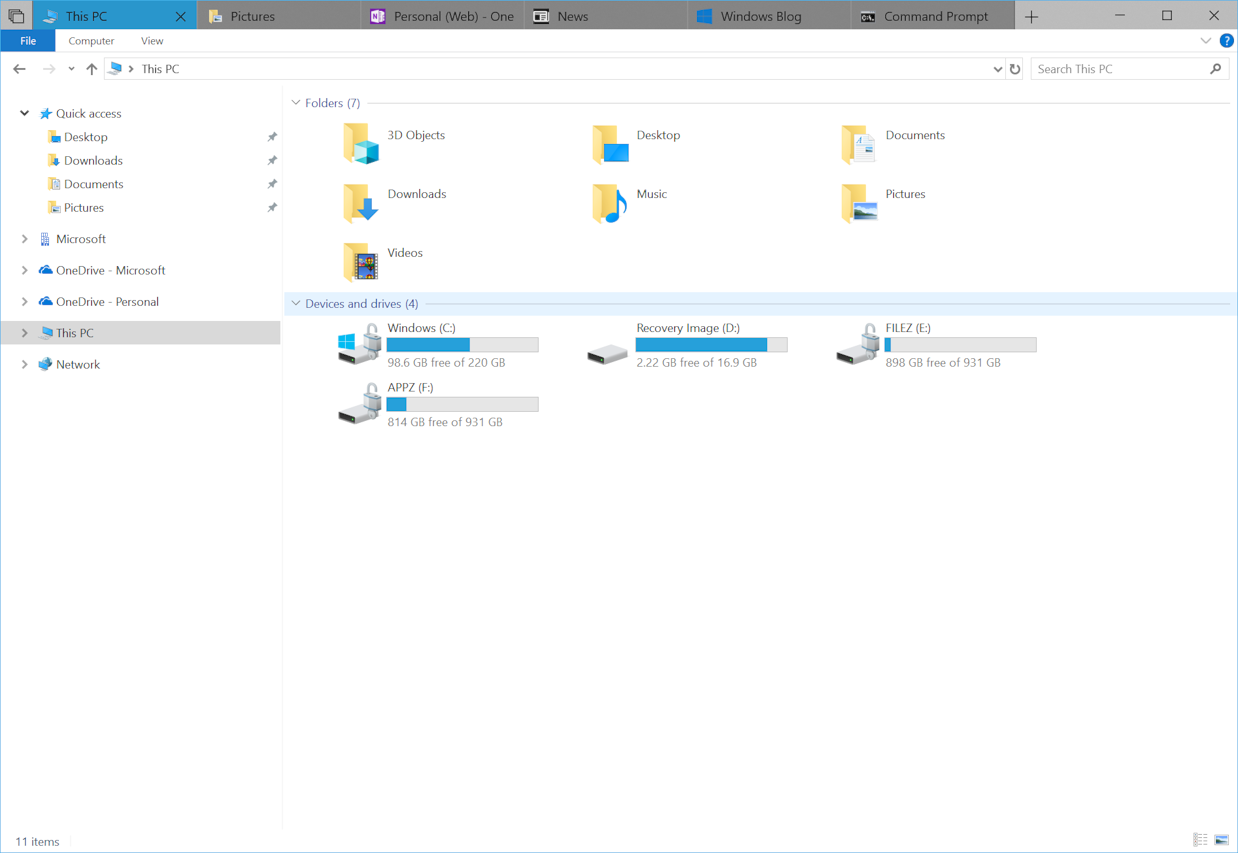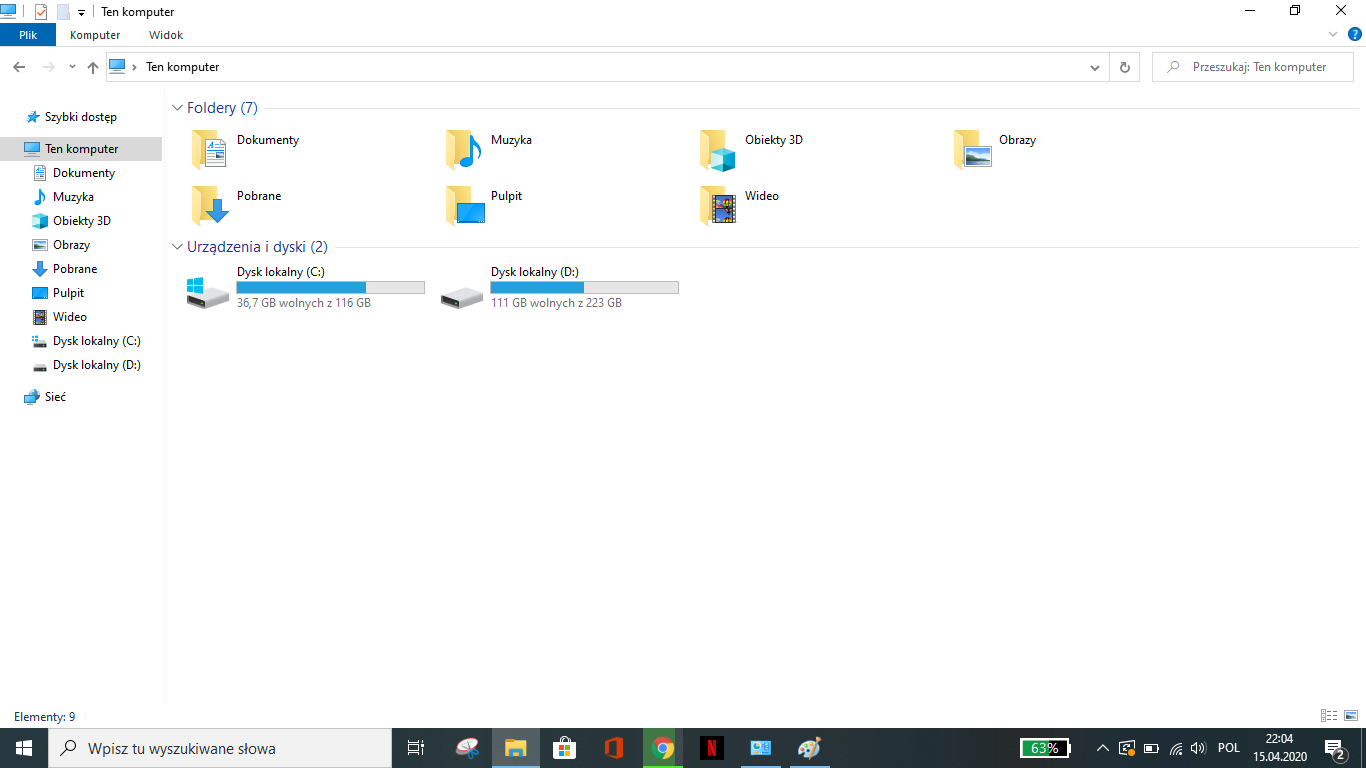
Co do języka to akurat przykład grafiki wyciągniętej z Google, ale taka sama czcionka jest też w języku polskim - zaciekawił mnie temat, kiedy korzystałem z innego laptopa. Co do sprawdzenia czcionki - niestety nie uda mi się jej sprawdzić w ten sam sposób. Znalazłem po prostu informacje, że domyślną czcionką w systemie Windows 10 jest właśnie Segoe UI i jednocześnie na dwóch obrazkach jest czcionka domyślna a tą samą Segoe UI być nie może. Jedyną chyba odpowiedzią dlaczego tak a nie inaczej jest wersja systemu Windows. Pomimo wszystko spróbuje wyciągnąć informacje o nazwie tej czcionki z innego komputera i sprawdzić czy jednak jest to ta sama czcionka Segoe UI, lecz różni się przez różne wersje systemu, czy ta czcionka jest inna. Dziękuje i pozdrawiam
Czcionka systemowa Windows 10 - Eksplorator plików
chciałbym zapytać z czego wynikają różnice wyglądu czcionki pomiędzy systemem na różnych urządzeniach. Wiem, że można ją zmieniać, ale zauważyłem, że domyślna nawet się różni. Załączam obrazki dla porównania. Poniżej ta którą mam ja - wyszukałem tyle że to jest Segoe UI.
Natomiast poniżej ta, która mnie interesuje - jest ona domyślna, nie zmieniana a inna :)
W związku z tym pytanie - co to za czcionka i skąd wynikają te różnice?
Chętnie podpowiem ws. różnic w wyglądzie czcionki Windows 10 na różnych urządzeniach.
Przyczyny różnic są następujące:
- Aktualnie używana wersja Windows 10 na komputerach. Sprawdzić to można, wpisując komendę winver w pole wyszukiwania obok przycisku Start i naciskając Enter. Dodam, że wersja systemu Windows 10 ma jeszcze specjalne oznaczenie np. Windows 10 Pro 1909, Windows 10 Education 1903, Windows 10 Home 1809. Wersje biznesowe, takie jak Enterprise lub Education mogą mieć ustawienia wg wymogów użytkownika, czyli m.in. wygląd standardowych czcionek może się różnić.
- Znaczenie mają również zainstalowane również domyślne ustawienia językowe. Na zdjęciach mamy ustawienia w językach polskim i angielskim, stąd również mogą wynikać różnice.
- Nazwa interesującej Cię czcionki nie jest mi znana. Jeżeli udało Ci się dowiedzieć, że czcionka na pierwszym zdjęciu ma nazwę Segoe UI, to w analogiczny sposób można sprawdzić nazwę czcionki na zdjęciu nr 2.